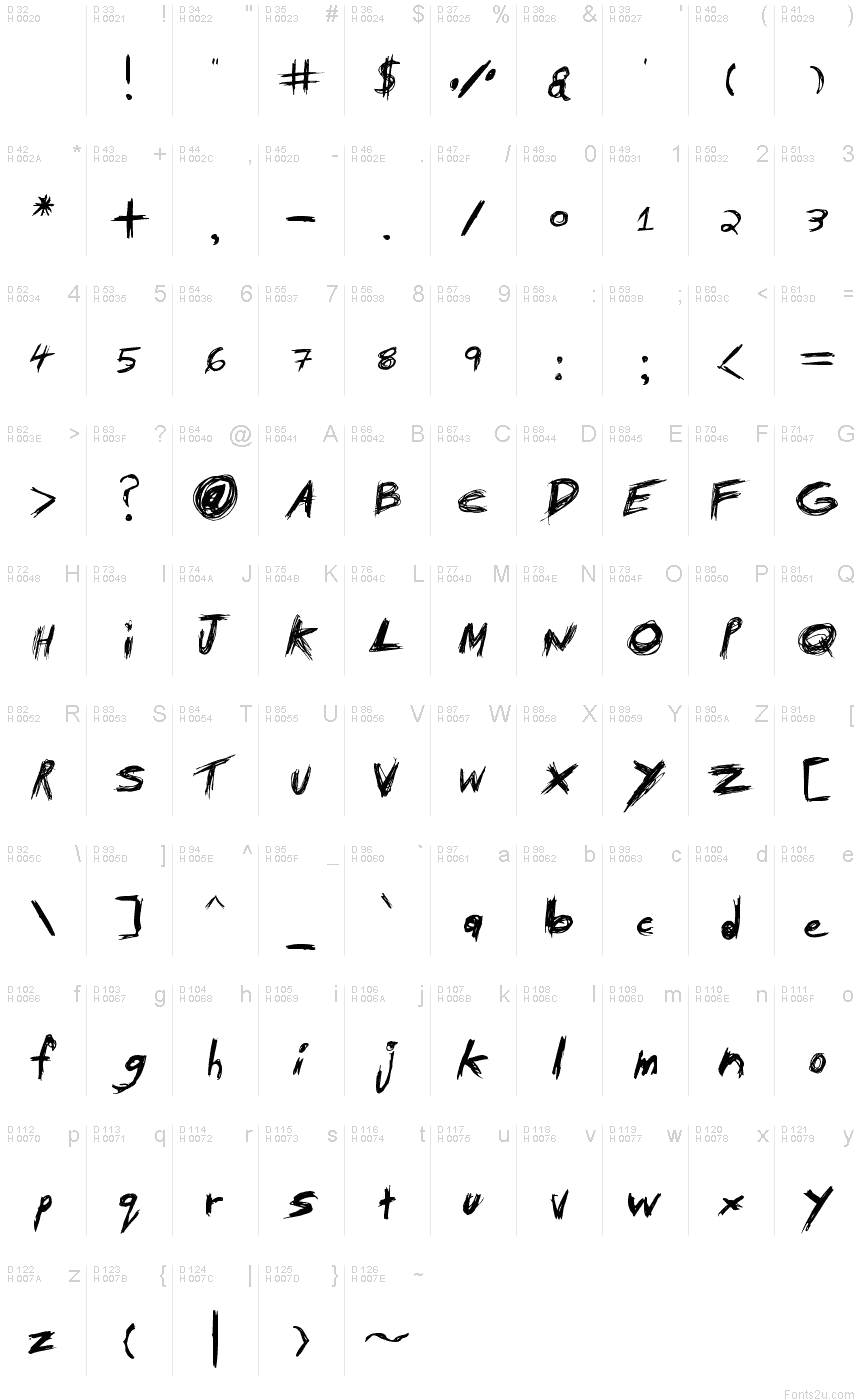
Tibetan Beefgarden AOE
Tibetan Beefgarden AOE, stworzony przez Astigmatic One Eye przy współpracy z Robertem Price’em, to darmowy font typu „trash brush” o surowym, poszarpanym charakterze. Litery sprawiają wrażenie wydrapanych w pośpiechu, z nerwowymi pociągnięciami, ostrymi haczykami i rozpryskami, co przywodzi na myśl estetykę punkowych ulotek, a nie schludną kaligrafię.
Świetnie sprawdzi się na plakatach muzycznych, okładkach zinów, w grafice deskorolkowej, horrorowych napisach i surowych nagłówkach redakcyjnych, wszędzie tam, gdzie font musi samodzielnie nieść ładunek emocji i dynamiki. Użyj go, gdy zależy Ci, aby krótkie słowa, linie okładkowe czy logo miały niespokojny, ręczny wygląd – tekstura pociągnięć załatwi sprawę.